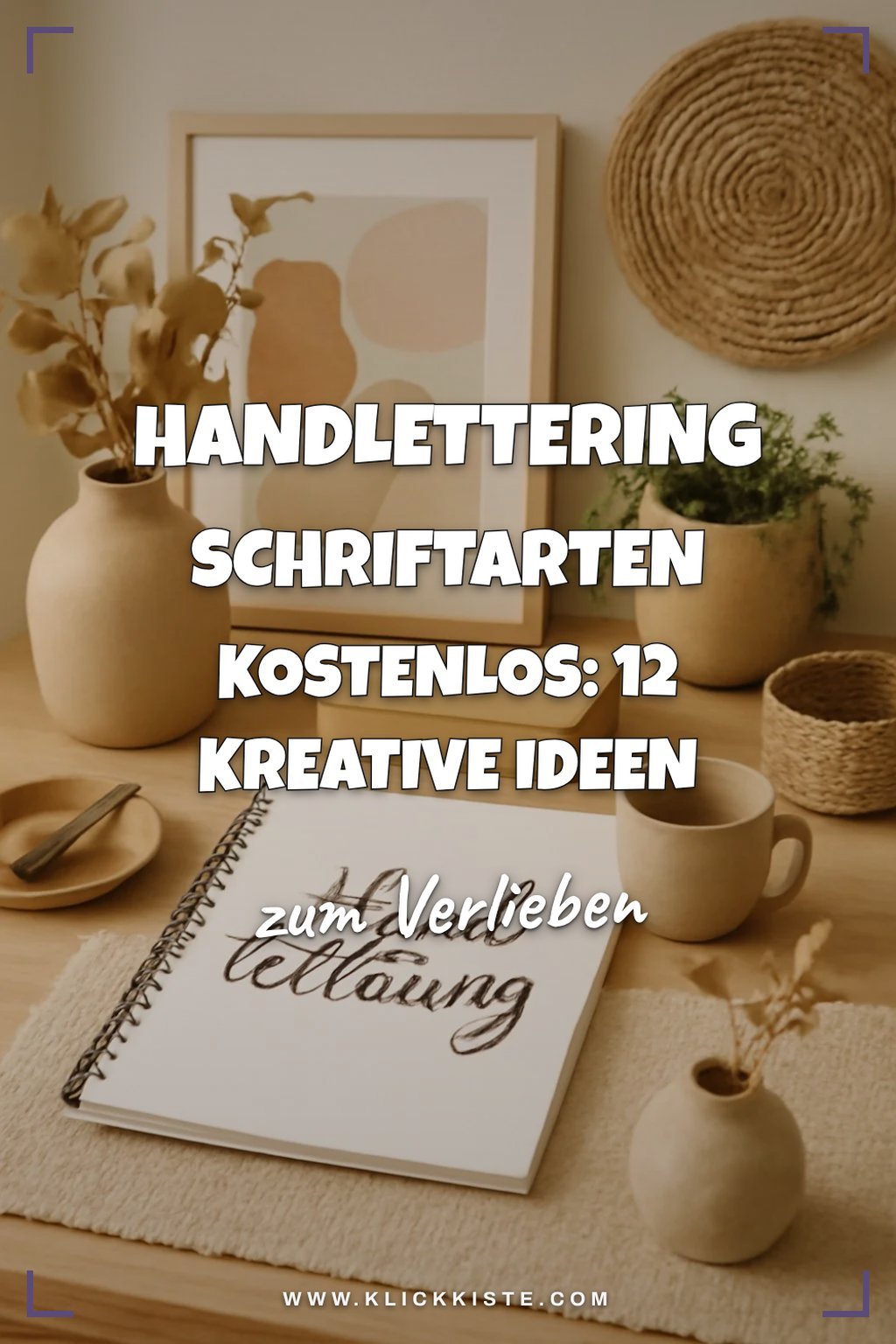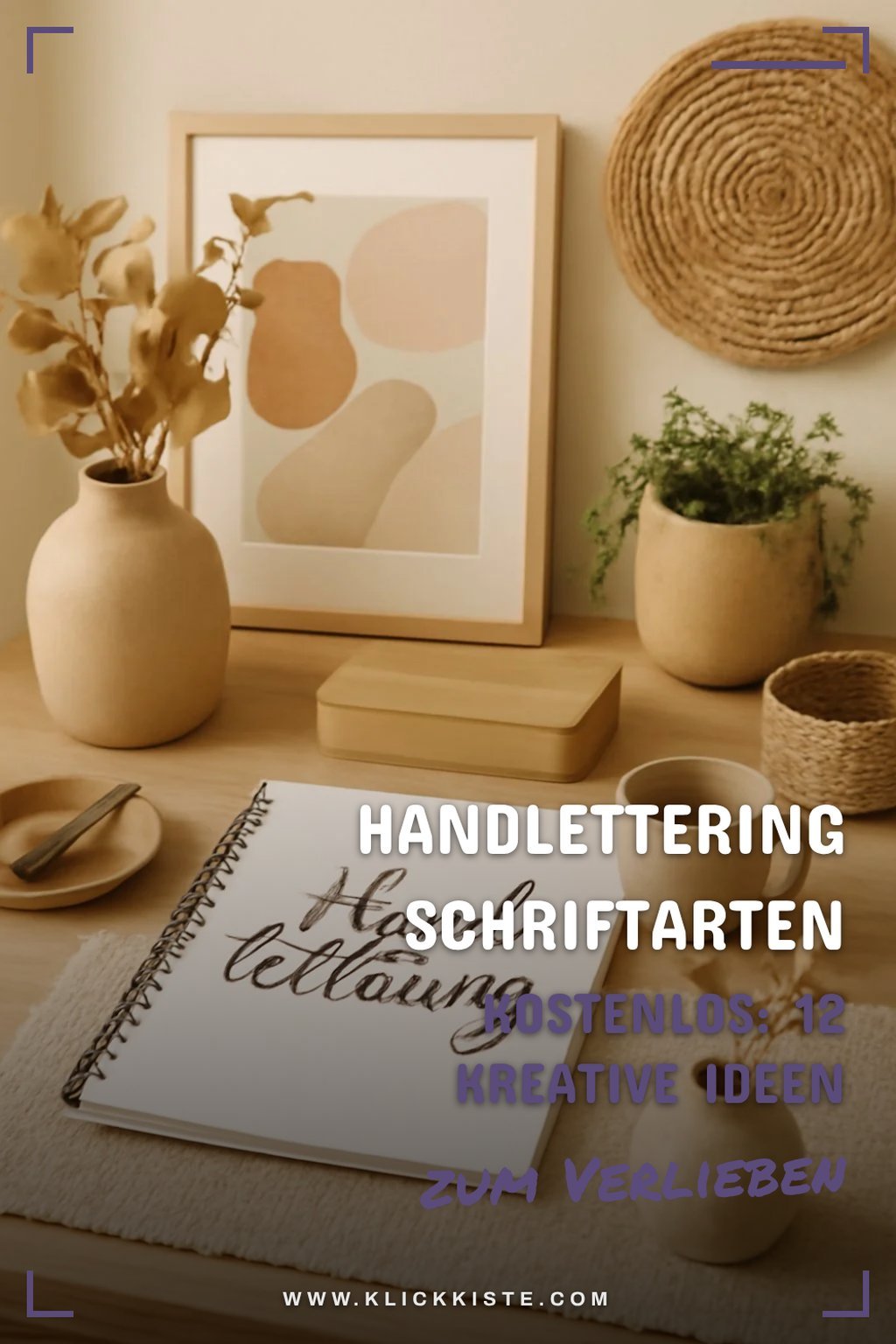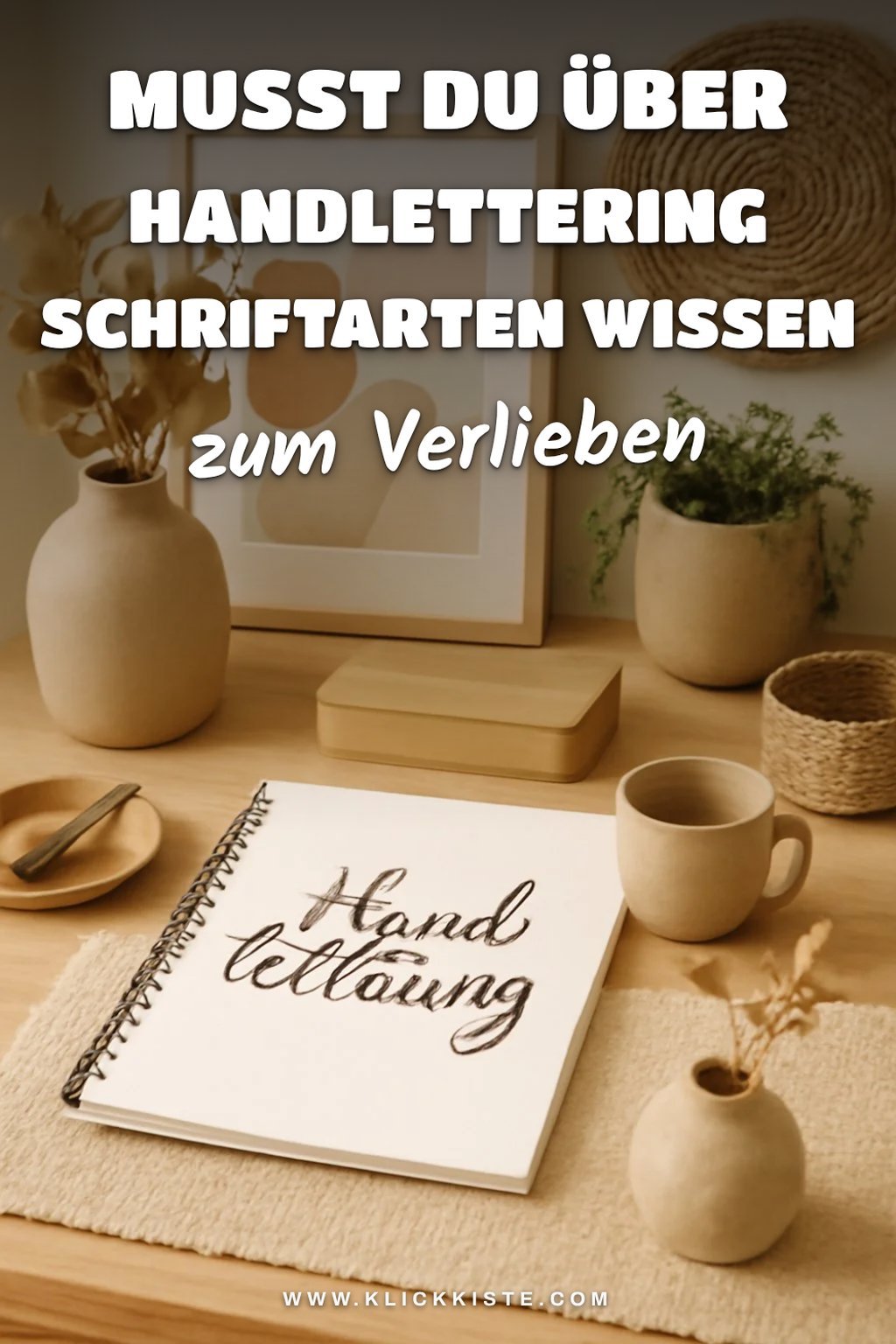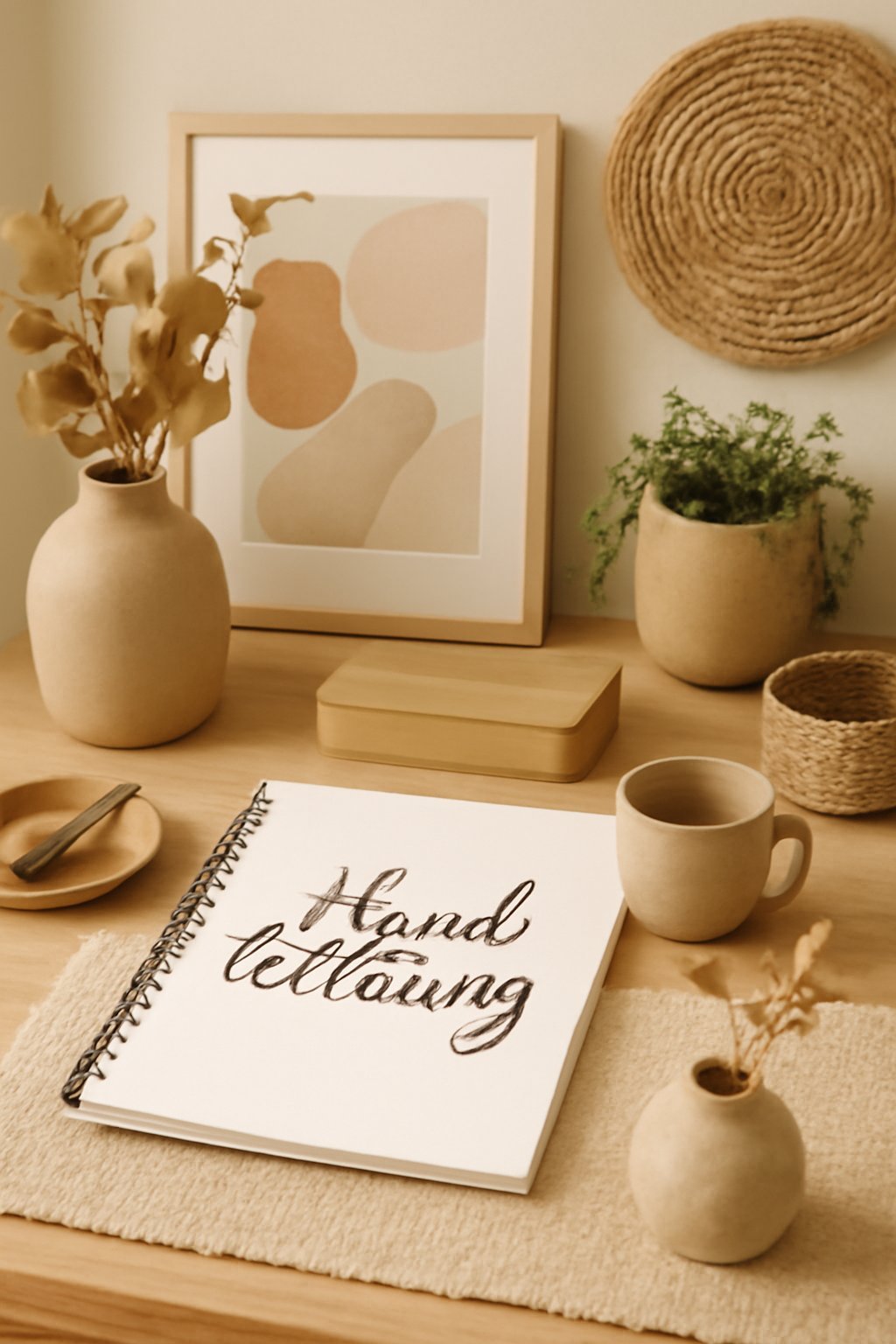
Warum Handlettering Schriftarten
Handlettering Schriftarten haben ihren Ursprung in der Kalligraphie und sind eine faszinierende Kunstform, die sich über die Jahre weiterentwickelt hat. Sie bieten eine Vielzahl an Variationen, die vom klassischen Schreibstil bis zu modernen, verspielten Formen reichen. Die Vielfalt an Stilen ermöglicht es dir, für jedes Projekt die passende Schriftart auszuwählen. Ob elegant, verspielt oder minimalistisch – jede Schriftart bringt ihren eigenen Charakter mit und kann deinem DIY-Projekt einen besonderen Touch verleihen. Ein weiterer interessanter Aspekt dieser Schriftarten ist ihre Vielseitigkeit. Handlettering findet nicht nur Anwendung auf Einladungen und Karten, sondern wird auch häufig in Dekorationen und persönlichen DIY-Projekten eingesetzt. In den Bewertungen wird oft erwähnt, dass die richtige Schriftart den Unterschied ausmachen kann. Es lohnt sich, beim Auswählen darauf zu achten, dass die Schrift einen harmonischen Einklang mit den restlichen Elementen deines Designs bildet. So entsteht eine stimmige Gesamtwirkung, die ansprechend und einladend wirkt.Handlettering Schriftarten Kostenlos: 12 kreative Ideen zum Selbermachen
- Beginne damit, einen Skizzenblock zu nehmen und ihn vor dir zu platzieren. Nimm den Bleistift zur Hand und skizziere grob die Buchstaben, die du gestalten möchtest.
- Sobald du mit deinen Skizzen zufrieden bist, nimm den Radiergummi und radiere vorsichtig die überflüssigen Linien aus.
- Jetzt ist es an der Zeit, die Buchstaben mit einem Fineliner nachzuziehen. Beginne mit den Umrissen der Buchstaben und arbeite langsam, um gleichmäßige Linien zu erzeugen.
- Wenn die Umrisse fertig sind, kannst du mit dem Marker Akzentuierungen setzen. Nutze verschiedene Strichstärken, um den Buchstaben mehr Charakter zu verleihen.
- Um die Schriftzüge zu perfektionieren, kannst du sie mit einem Lineal ausrichten. Dies sorgt dafür, dass alle Buchstaben gleichmäßig und ordentlich angeordnet sind.
- Lass die Tinte gut trocknen, bevor du die Seiten umblätterst oder die Schriftzüge verwendest. Dies verhindert, dass die Tinte verschmiert und sorgt für ein professionelles Finish.
- Jetzt kannst du deine Handlettering Schriftarten für verschiedene Projekte verwenden, sei es für Karten, Dekorationen oder Geschenke.
Gelingtipps
- Übe regelmäßig, um deine Fähigkeiten im Handlettering zu verbessern.
- Experimentiere mit verschiedenen Schriftarten und Stilen, um deinen eigenen Look zu finden.
- Nutze Vorlagen für komplexere Buchstaben, um den Einstieg zu erleichtern.
- Nutze einen hochwertigen Fineliner für ein besseres Ergebnis — er läuft gleichmäßiger und trocknet schneller.
- Halte die Hand beim Schreiben entspannt, um eine gleichmäßige Strichführung zu gewährleisten.
Variationsideen
- Kreativ: Verwende Wasserfarbe, um die Buchstaben zu kolorieren.
- Festlich: Gestalte die Schriftzüge für Einladungen zu Feierlichkeiten.
- Minimalistisch: Halte die Buchstaben einfach und klar ohne viel Schnickschnack.
Schritt 1
Beginne damit, einen Skizzenblock zu nehmen und ihn vor dir zu platzieren. Nimm den Bleistift zur Hand und skizziere grob die Buchstaben, die du gestalten möchtest. Achte darauf, dass die Buchstaben in der Größe und im Stil variieren, um interessante Effekte zu erzielen. So kannst du verschiedene Schriftarten ausprobieren und sehen, welche dir am besten gefällt. Lass deiner Kreativität freien Lauf und sei nicht zu streng mit dir selbst.
Schritt 2
Sobald du mit deinen Skizzen zufrieden bist, nimm den Radiergummi und radiere vorsichtig die überflüssigen Linien aus. Dies ist wichtig, um die Buchstaben klar und deutlich zu gestalten. Achte darauf, dass du die Formen der Buchstaben nicht beschädigst, während du die Hilfslinien entfernst. Ein sauberer Entwurf ist die Grundlage für das Handlettering.
Schritt 3
Jetzt ist es an der Zeit, die Buchstaben mit einem Fineliner nachzuziehen. Beginne mit den Umrissen der Buchstaben und arbeite langsam, um gleichmäßige Linien zu erzeugen. Achte darauf, dass du den Fineliner in einem gleichmäßigen Winkel hältst, um ein sauberes Ergebnis zu erzielen. Das Nachziehen gibt den Buchstaben mehr Tiefe und lässt sie lebendiger wirken.
Schritt 4
Wenn die Umrisse fertig sind, kannst du mit dem Marker Akzentuierungen setzen. Nutze verschiedene Strichstärken, um den Buchstaben mehr Charakter zu verleihen. Experimentiere mit Schattierungen und Farbverläufen, um die Schriftzüge interessanter zu gestalten. Achte darauf, dass die Farben harmonisch miteinander harmonieren und gut zusammenpassen.
Schritt 5
Um die Schriftzüge zu perfektionieren, kannst du sie mit einem Lineal ausrichten. Dies sorgt dafür, dass alle Buchstaben gleichmäßig und ordentlich angeordnet sind. Halte das Lineal an die Kanten der Buchstaben und ziehe eine Linie, um sicherzustellen, dass alles in einer geraden Linie ist. Eine saubere Ausrichtung macht einen großen Unterschied im Endergebnis.
Schritt 6
Lass die Tinte gut trocknen, bevor du die Seiten umblätterst oder die Schriftzüge verwendest. Dies verhindert, dass die Tinte verschmiert und sorgt für ein professionelles Finish. Geduld ist hier der Schlüssel, um die besten Ergebnisse zu erzielen.